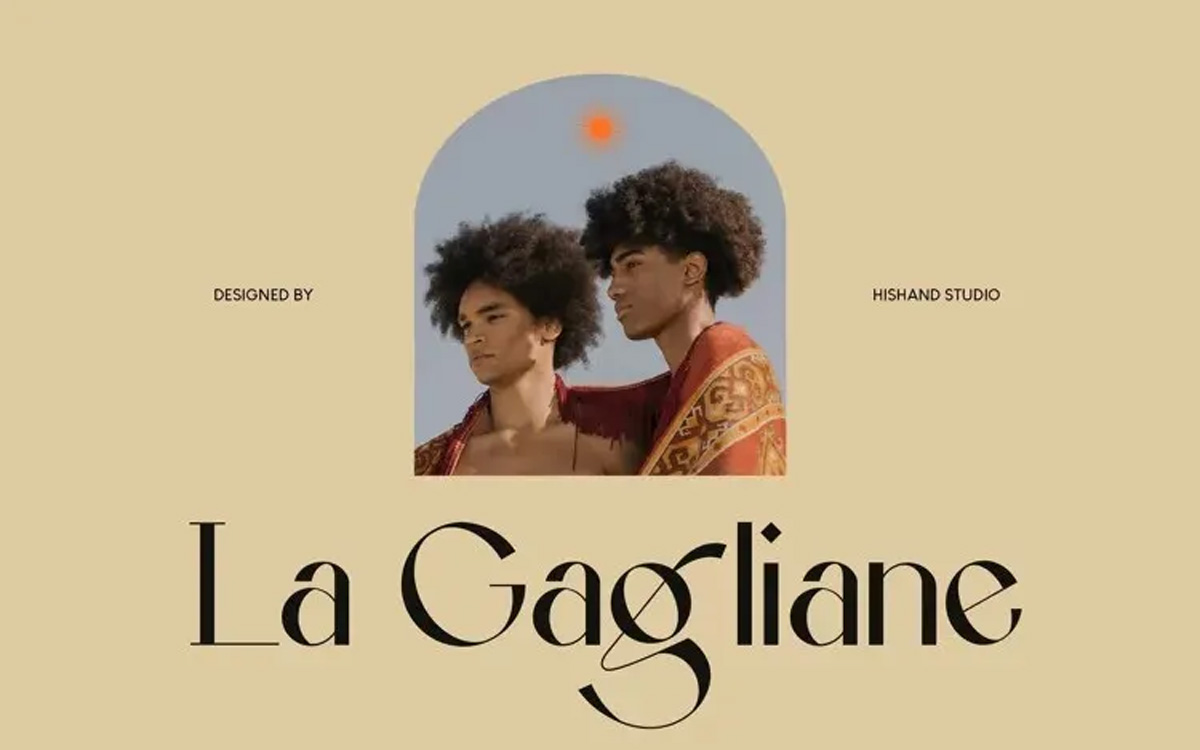
Font chữ thanh lịch, hiện đại, sang trọng dùng cho thiết kế thiệp cưới, thời trang, tạp chí TH La Gagliane
Trong thế giới thiết kế đồ họa đương đại, font chữ không chỉ đơn thuần là công cụ truyền tải thông điệp văn bản mà còn là “ngôn ngữ thị giác” định hình đẳng cấp và cảm xúc của tác phẩm. TH La Gagliane xuất hiện như một giải pháp typography đỉnh cao, dung hòa hoàn hảo giữa nét cổ điển thanh lịch và tinh thần hiện đại tối giản. Đây chính là sự lựa chọn không thể thay thế cho các nhà thiết kế đang tìm kiếm sự khác biệt sang trọng cho thiệp cưới, thương hiệu thời trang và các ấn phẩm tạp chí hàng đầu.
TH La Gagliane – Font Chữ Thanh Lịch, Hiện Đại Và Sang Trọng Đẳng Cấp Cho Thiết Kế Thiệp Cưới, Thời Trang Và Tạp Chí High-End
Để tạo nên một sản phẩm truyền thông thị giác gây ấn tượng mạnh ngay từ ánh nhìn đầu tiên, nhà thiết kế luôn cần những bộ font chữ sở hữu “thần thái” riêng biệt. Font chữ TH La Gagliane được nghiên cứu và phát triển dựa trên cảm hứng từ vẻ đẹp kiến trúc Ý lãng mạn kết hợp cùng xu hướng typography đương đại. Với cấu trúc chữ cân đối, đường nét mềm mại nhưng vẫn giữ được nét sắc sảo cứng cáp, TH La Gagliane dễ dàng chinh phục cả những chuyên gia art director khắt khe nhất trong ngành sáng tạo.
Sự tinh tế của TH La Gagliane không chỉ dừng lại ở mặt thẩm mỹ mà còn nằm ở khả năng ứng dụng vô cùng đa dạng. Dù xuất hiện trên chất liệu giấy mỹ thuật ép kim hay hiển thị trên màn hình kỹ thuật số độ phân giải cao, font chữ này vẫn giữ nguyên được độ nét, độ thoáng và đẳng cấp vượt thời gian.
1. Đường Nét Thiết Kế Tinh Tế, Đón Đầu Xu Hướng Typography Đương Đại
Điểm đặc trưng nhất của TH La Gagliane nằm ở tỷ lệ tương phản hoàn hảo giữa nét đậm và nét mảnh (thick-thin contrast). Sự tương phản này tạo nên hiệu ứng thị giác uyển chuyển, làm cho từng câu từ trở nên có nhịp điệu và sức sống nội tại.
• Nét chữ thanh thoát: Các đường cong được vuốt nhọn tự nhiên, tạo cảm giác nhẹ nhàng, bay bổng nhưng không quá ủy mị.
• Cấu trúc hình học chuẩn mực: Sự kết hợp giữa nét thẳng hiện đại và góc bo cổ điển giúp bộ font vừa có độ chắc chắn của xu hướng tối giản (minimalism), vừa có sự quý phái của phong cách hoàng gia.
• Khoảng cách kerning tối ưu: Bộ chữ được căn chỉnh khoảng cách tự động cực kỳ hợp lý, giúp việc dàn trang (layout design) trở nên nhanh chóng, giảm thiểu tối đa thời gian chỉnh sửa thủ công.
2. Giải Pháp Hoàn Hảo Cho Thiết Kế Thiệp Cưới Cao Cấp Và Ấn Phẩm Sự Kiện
Thiệp cưới là nơi lưu giữ khoảnh khắc trọng đại của đời người, đòi hỏi mọi chi tiết thiết kế phải tràn ngập tình yêu, sự trang trọng và nét lãng mạn. TH La Gagliane chính là mảnh ghép lý tưởng cho các bộ stationery cưới high-end.
Khi được sử dụng cho phần tên chú rể – cô dâu, các tiêu đề ngày cưới hoặc thiệp mời sự kiện sang trọng, font chữ thể hiện trọn vẹn nét ngọt ngào và kiêu sa. Tỷ lệ đường nét của font rất thích hợp để gia công in ấn sau thành phẩm như: ép kim nổi (foil stamping), dập chìm (embossing), hoặc in kéo lụa trên các chất liệu giấy nhám, giấy mạ vàng hay mica trong suốt.
3. Linh Hồn Cho Nhãn Hàng Thời Trang, Mỹ Phẩm Và Layout Tạp Chí Chuyên Nghiệp
Đối với ngành công nghiệp thời trang và làm đẹp, font chữ đóng vai trò tuyên ngôn cho cá tính thương hiệu. TH La Gagliane mang trong mình hơi thở của các nhà mốt Paris và Milan, dễ dàng biến mọi ấn phẩm truyền thông thành một tác phẩm nghệ thuật thượng lưu.
• Thiết kế Logo & Identity: Thích hợp làm logo nhận diện cho các thương hiệu thời trang cao cấp, spa, mỹ phẩm xa xỉ, tiệm trang sức hoặc dòng nước hoa niche.
• Bìa Tạp chí & Editorial: Tạo nét nhấn nhá đầy quyền lực cho tiêu đề bài viết, trang bìa (cover magazine), lookbook giới thiệu bộ sưu tập thời trang mới.
• Bao bì sản phẩm: Nâng tầm giá trị cho vỏ hộp, nhãn chai, mang lại cảm giác đắt giá và đáng tin cậy cho người tiêu dùng.
4. Tích Hợp Bộ Ký Tự Việt Hóa Chuẩn Tỷ Lệ Và Tính Năng OpenType Đa Dạng
Một ưu điểm vượt trội không thể bỏ qua của bản TH La Gagliane Việt hóa là sự tỉ mỉ trong việc thiết kế dấu tiếng Việt. Khác với các font chữ việt hóa sơ sài thường bị hỏng tỷ lệ hoặc dấu thanh quá to/nhỏ làm phá vỡ cấu trúc dòng chữ, TH La Gagliane được tinh chỉnh dấu thanh cực kỳ hài hòa với tổng thể bộ chữ.
Bên cạnh đó, font chữ còn đi kèm hệ thống tính năng OpenType phong phú bao gồm các ký tự thay thế (stylistic alternates), ký tự nối (ligatures) và ký tự trang trí đuôi chữ (swashes). Nhờ đó, các designer có thể tự do sáng tạo biến tấu hàng trăm kiểu kết hợp chữ khác nhau mà không lo trùng lặp ý tưởng.
5. Khả Năng Hiển Thị Hoàn Hảo Trên Cả Ấn Phẩm In Ấn Lẫn Kỹ Thuật Số
Trong thời đại chuyển đổi số, một font chữ đẹp cần phải vận hành tốt trên cả phương diện in ấn truyền thống và hiển thị màn hình (digital display). TH La Gagliane đáp ứng hoàn hảo yêu cầu này nhờ thuật toán tối ưu hóa nét vẽ dạng vector chuẩn xác.
Dù xuất hiện trên banner website e-commerce, bài đăng Social Media (Instagram, Facebook), ứng dụng di động hay trên các biển hiệu quảng cáo tấm lớn (billboard), font chữ vẫn giữ được độ sắc nét tuyệt đối, không bị vỡ nét hay gây mỏi mắt cho người đọc.